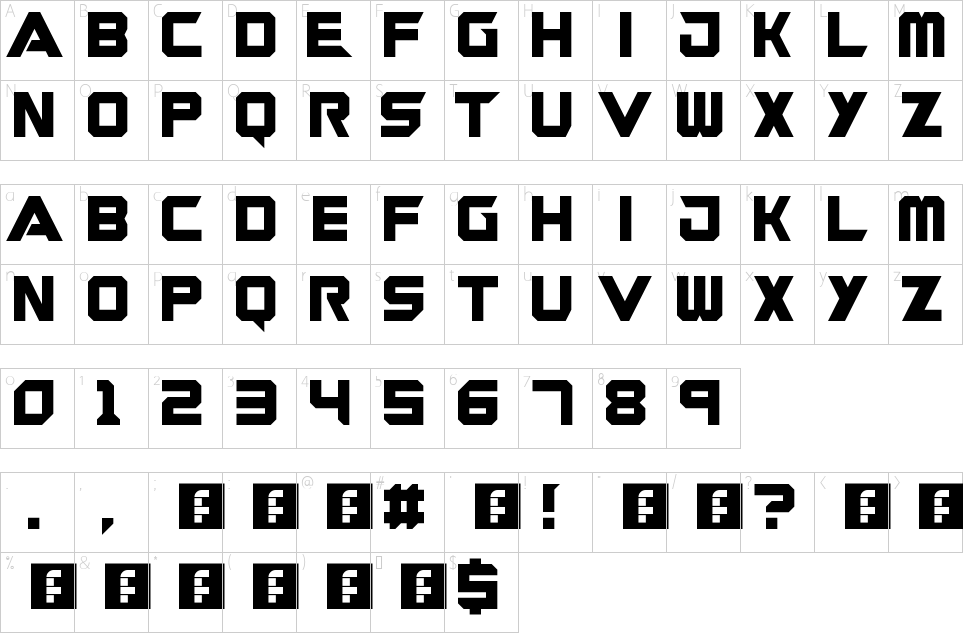
Aguardantes Font é uma elegante escolha para designers digitais atentos à qualidade. Desenhada por Geronimo Fonts, esta font gratuita pode ser baixada tanto no sistema Windows quanto no Mac. Seu design minimalista e sofisticado torna-a perfeita para texturas de logotipos, sites profissionais ou qualquer projeto que busque uma apresentação moderna e limpa. Com a capacidade de personalização completa e sem custo nenhum, o Guardians Font se destaca como um recurso valioso para designers iniciantes e experientes. Desde sua disponibilização inicial em 2018, a font tem sido baixada mais de 15.920 vezes, indicando seu valor único na comunidade de design digital. Se você está procurando por uma maneira fácil e gratuita de adicionar um toque singular ao seu trabalho, Guardians Font é o seu próximo passo.